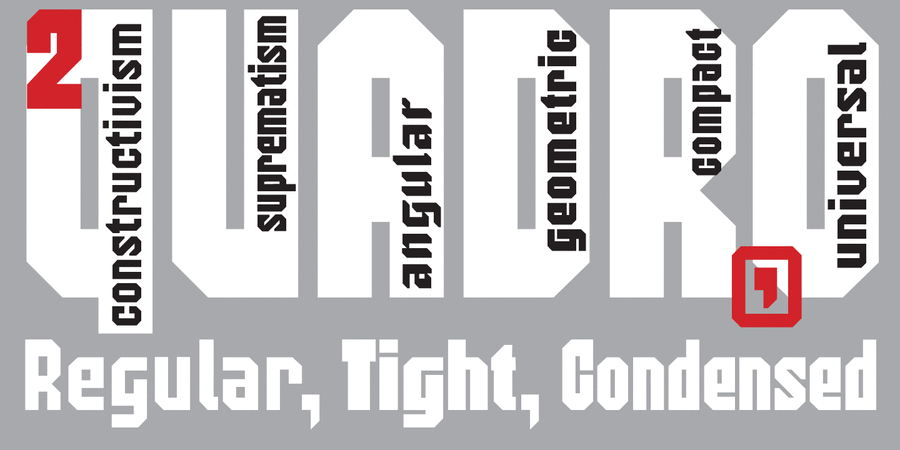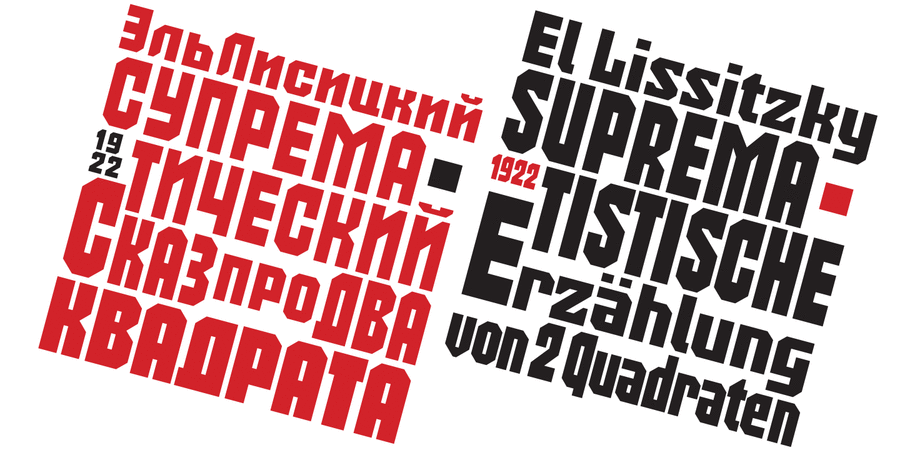
2Quadro (8 шрифтів)
Ця ґарнітура узагальнює та розвиває традицію грубих квадратизованих підрізаних під 45° ґротесків, відомих ще з середини 19 століття, що їх активно вживали у різні часи (нп. у 1920-ті, 1970-ті) та продовжують нині завдяки грубуватій виразності, монументальності та можливості максимально заповнювати площину не втрачаючи читабельності. Добре пристосована для підкладання світлин під літери та створення геометричних конструктивістських композицій. Шрифт розробив Віктор Харик у 2014 році.
Асоціації з сімейством шрифтів 2QuadroОсобистість і характер гарнітури:
важкий, авторитетний, значний, серйозний, переконливий, твердий, залізний, надійний, мужній, впевнений, сталевий, грубий, ностальгічний, тоталітарний, гучний, рівний, сильний, кондовий, стійкий, політичний, комуністичний, революційний, сміливий, пролетарський, тісний, стиснений, щільний, важливий, точний, прямокутний, індустріальний, техногенний, військовий, армійський, червоний, монументальний, солдатський, урбаністичний, робочий, мотивуючий, амбітний, суворий, блатний, помітний, яскравий, активний, крутий, залізничний, міський, інженерний, статичний, автоматичний, креслярський, брутальний, кричущий, потужний, електронний, квадратний, холодний, різкий, чіткий, машинний, космічний, промисловий, ламаний, незграбний, гранчастий, міцний, радикальний, рубаний, спортивний, ігровий, чорний, високий
війна, армія, зброя, машинобудування, прапор, мітинг, політика, шахта, завод, металургія, танк, тренажери, верстат, інструмент, будівництво, будматеріали, тара, склад, порт, ящик, патрони, архітектура, конструктор, креслення, техніка, промисловість, електростанція, енергетика, революція, ремонт, урбаністика, депо, шахтар, шолом, уніформа, вагон, страйкбол, блокбастер, бойовик, екшен, взуття, цегла, мотор, двигун, залізниця, Місто, інженер, автоматика, Футбол, робочий, страйк, Протест, екскаватор, електроніка, авто, робот, гра, космос, автомат, шутер, охорона, захист, паливо, залізо, фантастика, сталевар, кіно, Локдаун, комп'ютерна гра, спорт, кубики, лего, супергерой Гарнітура має ознаки стилів: